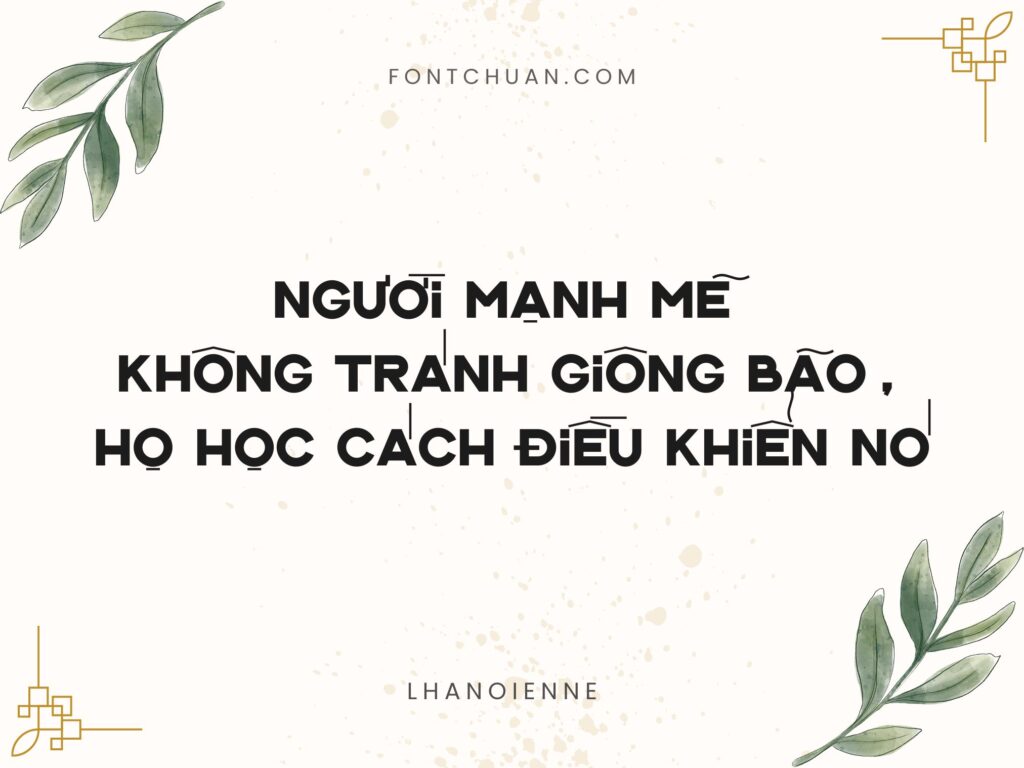
L’Hanoienne là một Font sans-serif được thiết kế bởi Mạnh Nguyễn, một nhà thiết kế chữ người Việt Nam. Phông chữ này lấy cảm hứng từ phong cách cổ điển của các bảng hiệu và biểu ngữ vẽ tay, từng là biểu tượng trên đường phố Việt Nam trong thế kỷ 20. Sau thành công của Classique Saigon, Mạnh Nguyễn tiếp tục dự án của mình với L’Hanoienne để tôn vinh vẻ đẹp của Hà Nội. Mặc dù chia sẻ kiểu dấu và cấu trúc chữ với Classique Saigon, L’Hanoienne có những khác biệt đáng kể ảnh hưởng đến trải nghiệm đọc. Được xây dựng như một sans-serif hình học hiện đại, L’Hanoienne có độ tương phản nhẹ và cấu trúc tinh tế hơn, phản ánh vẻ đẹp kín đáo và dịu dàng của phụ nữ Bắc Kỳ thế kỷ 20. Phông chữ này đã được Việt hóa bởi chính tác giả, hỗ trợ đầy đủ các ký tự tiếng Việt, mang lại trải nghiệm gõ chữ trọn vẹn cho người dùng Việt Nam. Ngoài tiếng Việt, L’Hanoienne còn hỗ trợ nhiều ngôn ngữ khác, mở rộng khả năng ứng dụng trong các dự án quốc tế.
Nhờ sự kết hợp giữa phong cách hoài cổ và tính hiện đại, L’Hanoienne không chỉ phù hợp cho các thiết kế mang hơi thở truyền thống mà còn có thể được ứng dụng như một Font chữ Công nghệ. Điều này giúp nó trở thành lựa chọn linh hoạt cho các dự án UI/UX, website, ứng dụng di động hay các sản phẩm truyền thông số, nơi cần sự hài hòa giữa tính thẩm mỹ cổ điển và sự hiện đại công nghệ.
Về đặc điểm thiết kế, L’Hanoienne có cấu trúc sans-serif hình học với độ tương phản nhẹ, tạo cảm giác mềm mại nhưng vẫn hiện đại. Phông chữ này phù hợp cho các ứng dụng như thiết kế logo, tiêu đề, thương hiệu lấy cảm hứng cổ điển, biển hiệu và các dự án sáng tạo khác. L’Hanoienne cũng thích hợp cho các thiết kế cần sự tinh tế và hiện đại, như áp phích quảng cáo, bao bì sản phẩm và các dự án truyền thông. Về ngành nghề, L’Hanoienne đặc biệt phù hợp với lĩnh vực quảng cáo, công nghệ, giáo dục và các ngành nghề cần sự sáng tạo và hiện đại trong thiết kế. Sự linh hoạt và tinh tế của phông chữ giúp nó dễ dàng hòa nhập vào nhiều phong cách thiết kế khác nhau, từ cổ điển đến hiện đại.